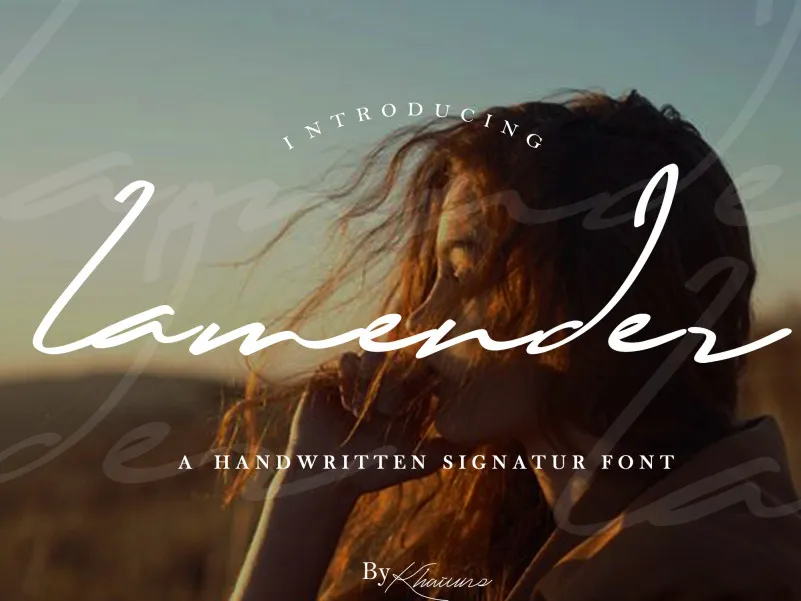
Lamender Handwritten Font – Download Grátis
A Lamender Handwritten Font é uma escolha perfeita para quem busca adicionar um toque autêntico e envolvente às suas criações digitais. Inspirada na arte do xilogravura, essa fonte de letra escrita à mão oferece linhas suaves e detalhes elegantes que vão desde nomes simples até textos mais elaborados. Com o design delicado de uma calligrafia real, a Lamender Handwritten Font proporciona um acabamento personalizado para qualquer projeto digital ou impresso. Se você é artista gráfico, designer de moda ou criativo em geral, essa fonte é certamente algo que você deve conhecer e considerar para suas necessidades de design. Agradecemos sua compreensão ao usar a demo gratuita desta fonte, e qualquer contribuição adicional é sempre bem-vinda por meio do PayPal.
Designer: khaiuns